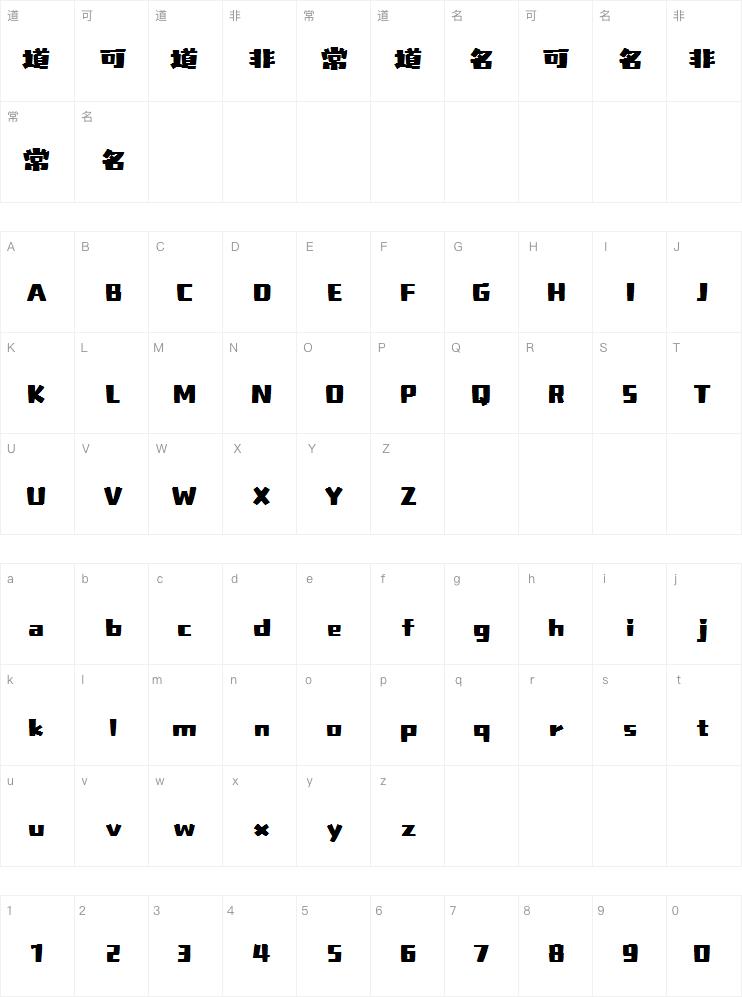
山海奶酪布丁w
山海奶酪布丁,是一款全新的字体,包含汉字9169个,符号200+个。该字体是一款卡通风字体,该字体字形灵动多变,童趣可爱,结构多变灵动,字形活泼清新,造型生动有趣,具有灵活的适用性,天真俏皮又不失时尚感。该字体字形重心一致,字取横势,笔触方中带圆,笔画布局在多变的同时有保持整体均衡匀称。一个个方形且圆润的笔画如一块块奶酪造型,可爱且灵动。字形比例按照宽高5:4的比例设计,使得字体显得敦厚。灵动笔画贯穿笔画始终,内涵丰富,弧度柔和,撇笔平缓舒展,尽显俏皮灵动。